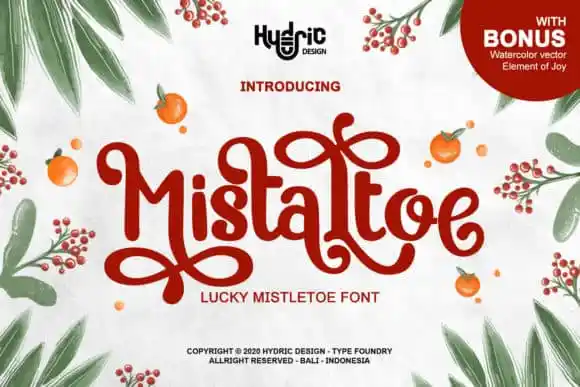
Mistaltoe Display Font – Fonte Grátis
Mistaltoe Display Font
Mistaltoe Display Font é uma fonte de san serif que combina influências tradicionais com um olhar contemporâneo. Este script elegante e sofisticado traz uma atmosfera única ao seu design, adaptando-se perfeitamente para estilos gráficos modernos sem perder sua simplicidade e beleza. Ideal para aplicar em nomes de empresas ou marcas, mistérios e identidades visuais que valorizam uma linguagem arredondada e moderna. Mistaltoe Display Font é um complemento perfeito para qualquer projeto gráfico buscando aquela personalidade única, combinando a elegância dos tempos antigos com o frescor da contemporaneidade. Designer responsável: HydricDesign